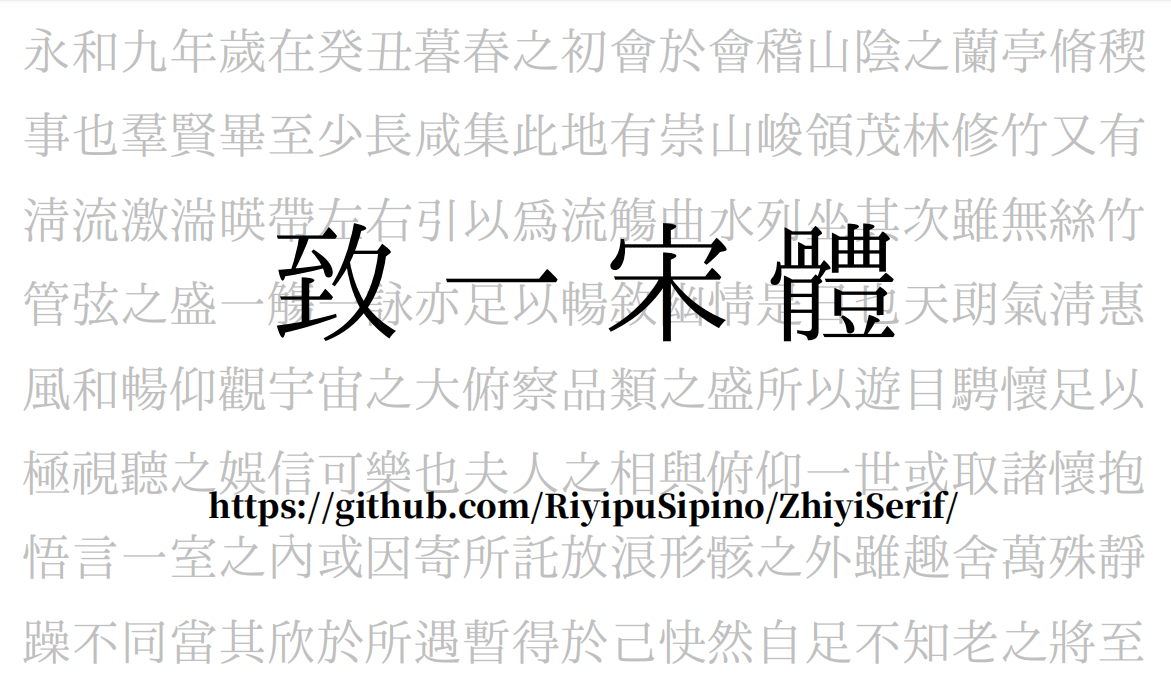
致一宋体 ZhiyiSerif 致一宋體
虽世殊事异,所以兴怀,其致一也。 ——《兰亭集序》
「致一宋体」是一套以 TrueType 格式封装、依照 Unicode 编码的 OpenType 字型,采用「 怀有传承字形向往的自订新字形 」,即以传承和惯用字形为主体、多就少改,兼以传承字形笔法为基础,参考历史异形、类推隶定规则,制订新的字理部件,力使字理直观、优化、可分 (注:优先取用传世字理和强势初理) ,字形通行、美观、可认、兼顾写印 。
避免隶古定,且尽可能区别字源、统一部件;既求字理直观清晰,也求字形美观通用
「致一宋体」本为作者自创世界观的字型, 初心即是区别字源、统一部件 。最初的字形有大量初文本字,虽合古意,但是「似篆非隶,若存若亡」,体系复杂,辨识度差,自己读写都慢,就更不要指望那个世界观的角色们会用了。
纵观汉字发展史,字理本不可知、还要后人考证者有之,初理本不可知、千年来已有重构新字理、弃去实在可惜者有之,本系同音、近音甚至同义假借(如「开」,本读作{启},训读为{闿}),「鸠占雀巢」甚至「鸠占鸠巢」者有之,即便身世清楚,直接把字源堆到一起的「古字」大众根本不识(如「⿱爫象」,今作「为」)者亦有之。
究其原因,今人所书虽去古渐远,然笔画增损之间,实有潜藏理路可循。一曰隶今定法则 ,二曰理据重构 。隶今定法则——即「现代隶定规律」——不是一对一的,而是一对多、多对一的。例如「出」「大」,作部件时多简写为「士」「土」——字理上的「出」「大」不一定写成「出」「大」,字形上的「士」「土」也未必就是「士」「土」。重构理据更是汉字传承的生命力所在。例如「幸」字,本从犬、从倒矢,理据不明,今则从夭从屰(逆),理据昭然。
传承字形是隶今定法则的结晶 ,经宋明以来历代文字学者整理,已具备高度的一致性和区分性。不过,随着考古学和文字学的进一步发展, 以前的某些字形已经不再是最优解 。例如,出土简帛的声部件,左上角从士形、从石,若取书法形体,理据重构从十形、从石,则比印刷体异变后的纯象形理据更直观;现代文字学已经证明,「益」与(「溢」之右)并不相同,而传承字形虽有两种不同写法(「益」与「益」),却受当时的学术所限,相互混作,并未特意分开。
正式版谨守隶今定法则、尊重理据重构,并经多番考量,最终决定:以传承字形为基础,以约定俗成为准则,多就少改、应改即改,让字源和重构理据公平竞赛, 既求字理直观清晰,也求字形美观通用 。不独是为了自创世界观的角色,亦是为了做一份文字学答卷,请天下有缘之士批评指正。
包含原版、适当扩大字面的报刊版、适当加粗的屏幕阅读版、加粗且扩大字面的屏幕报刊版。